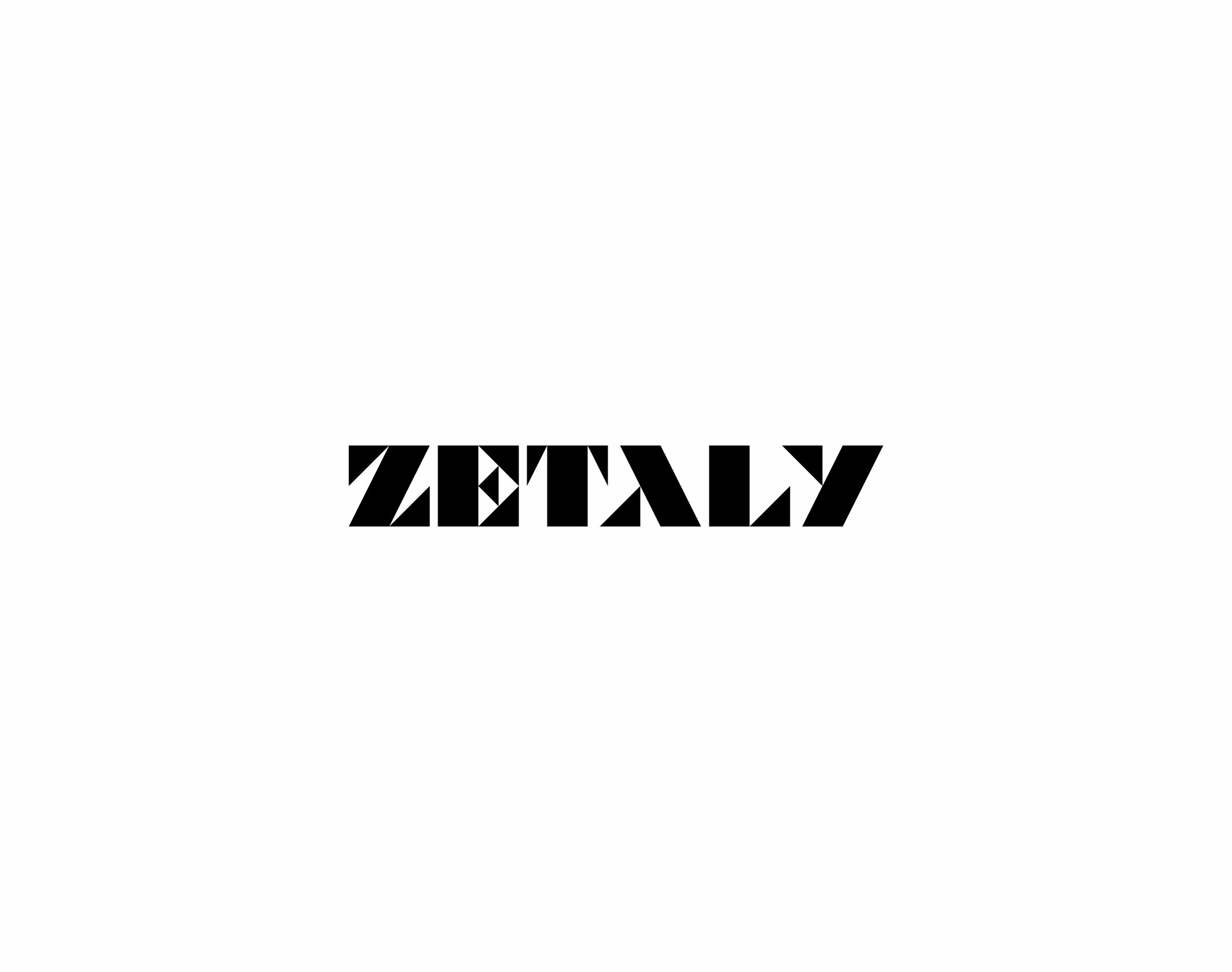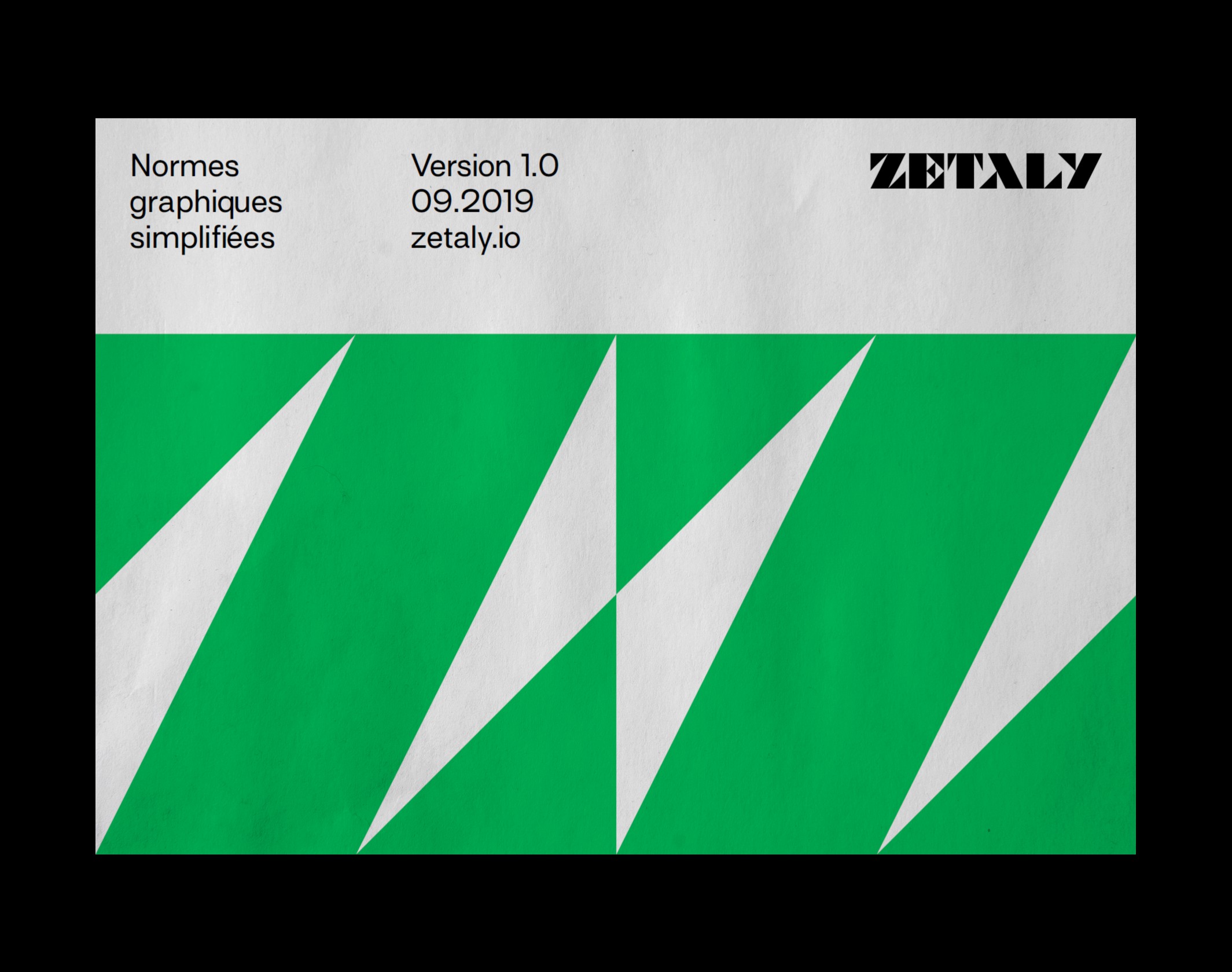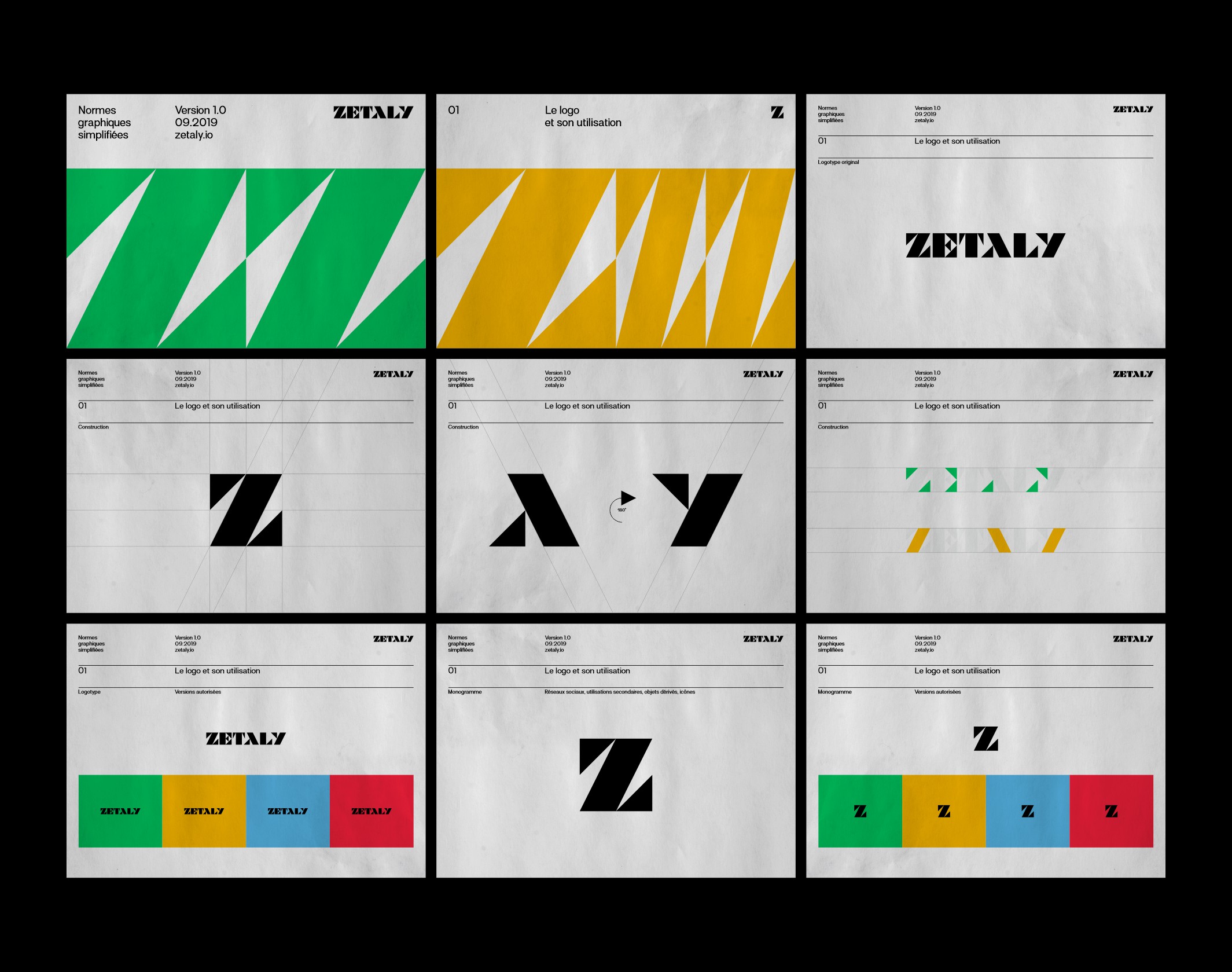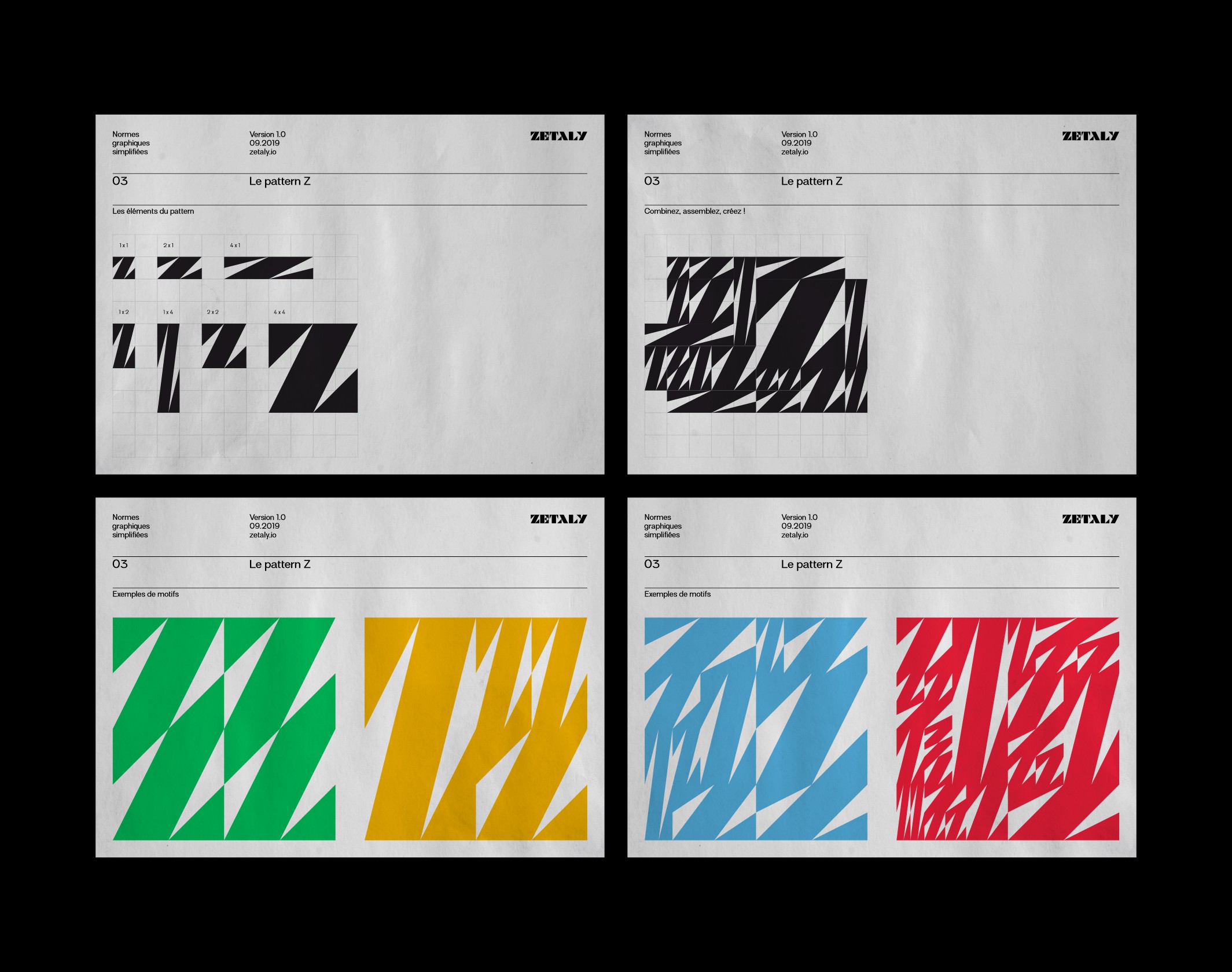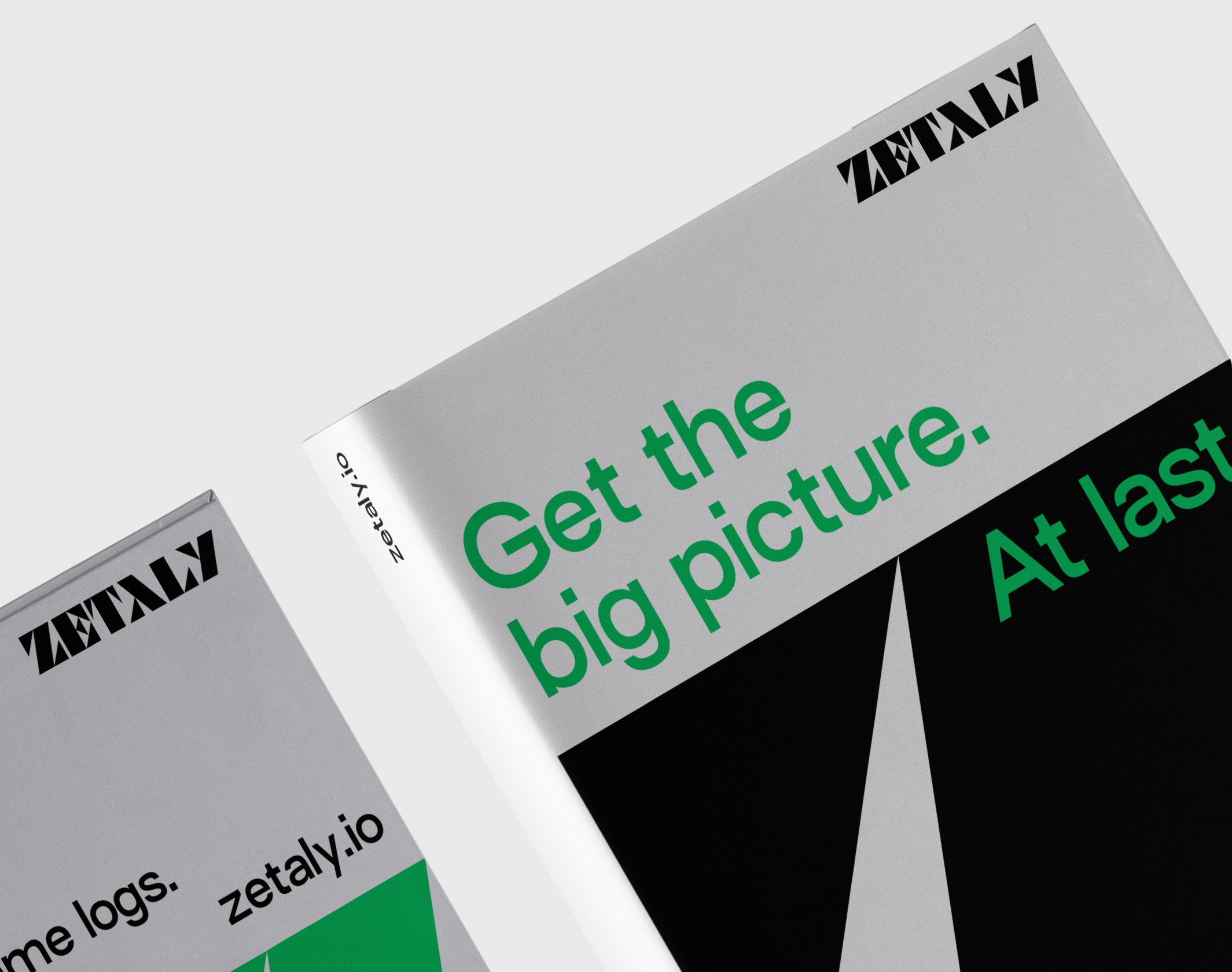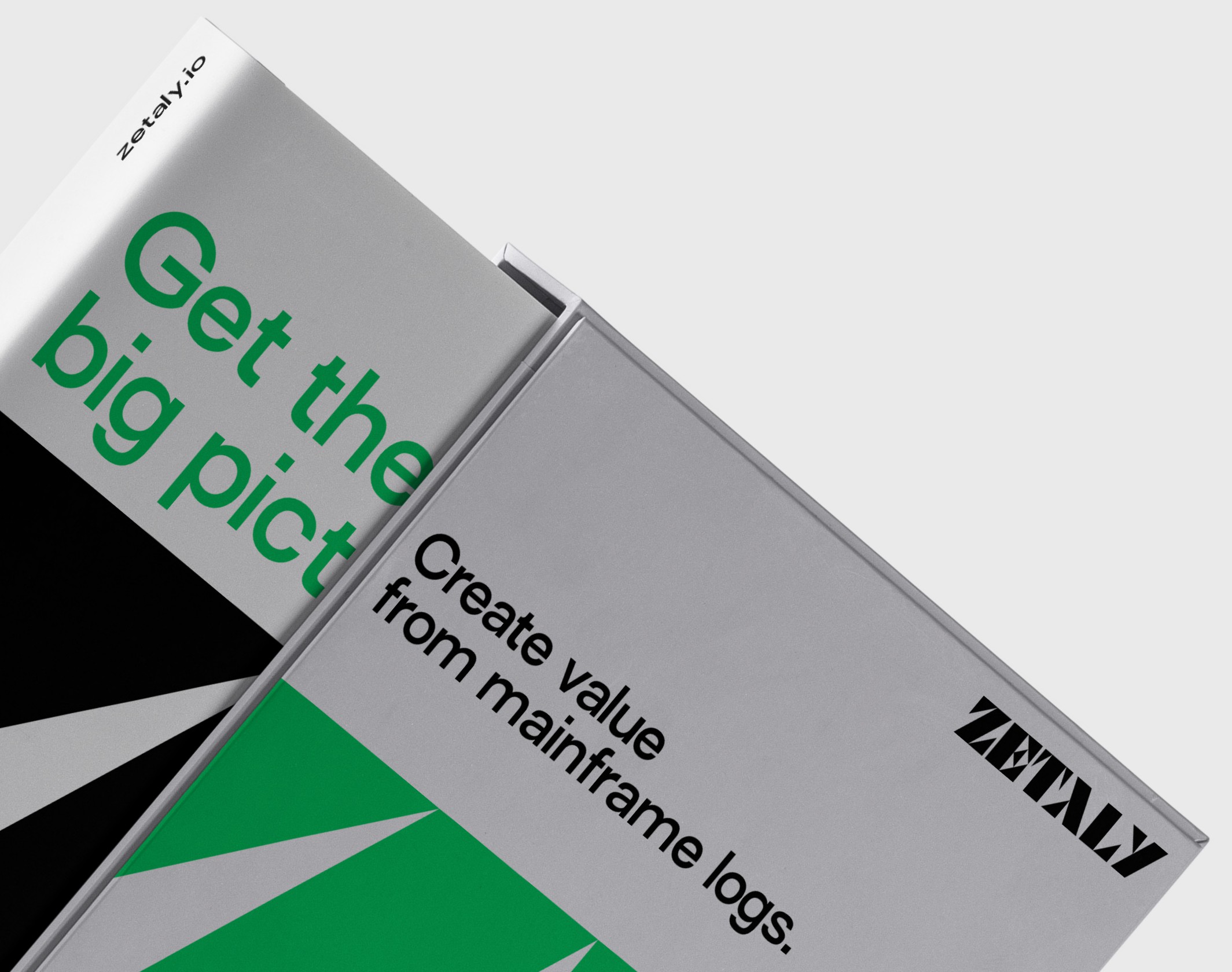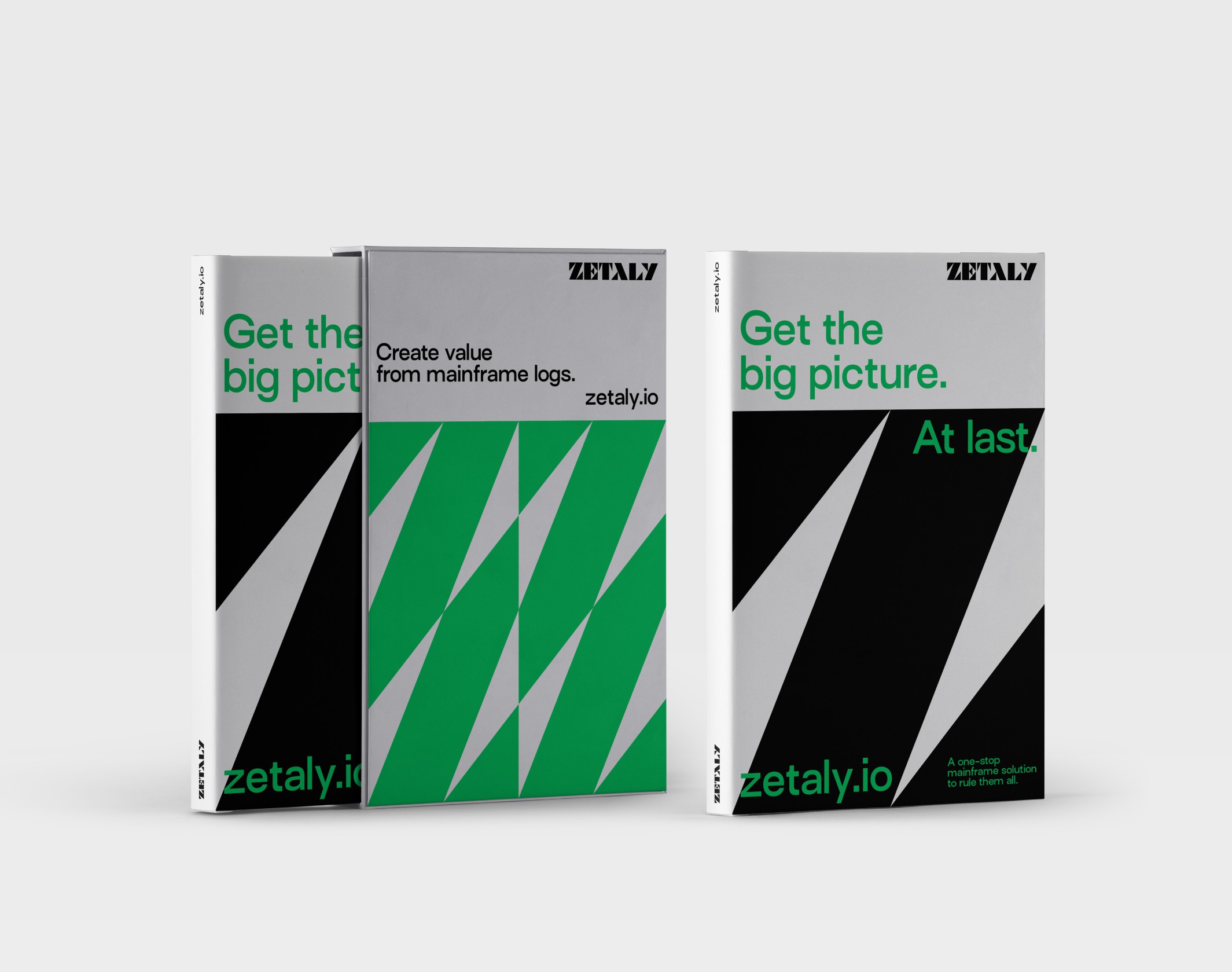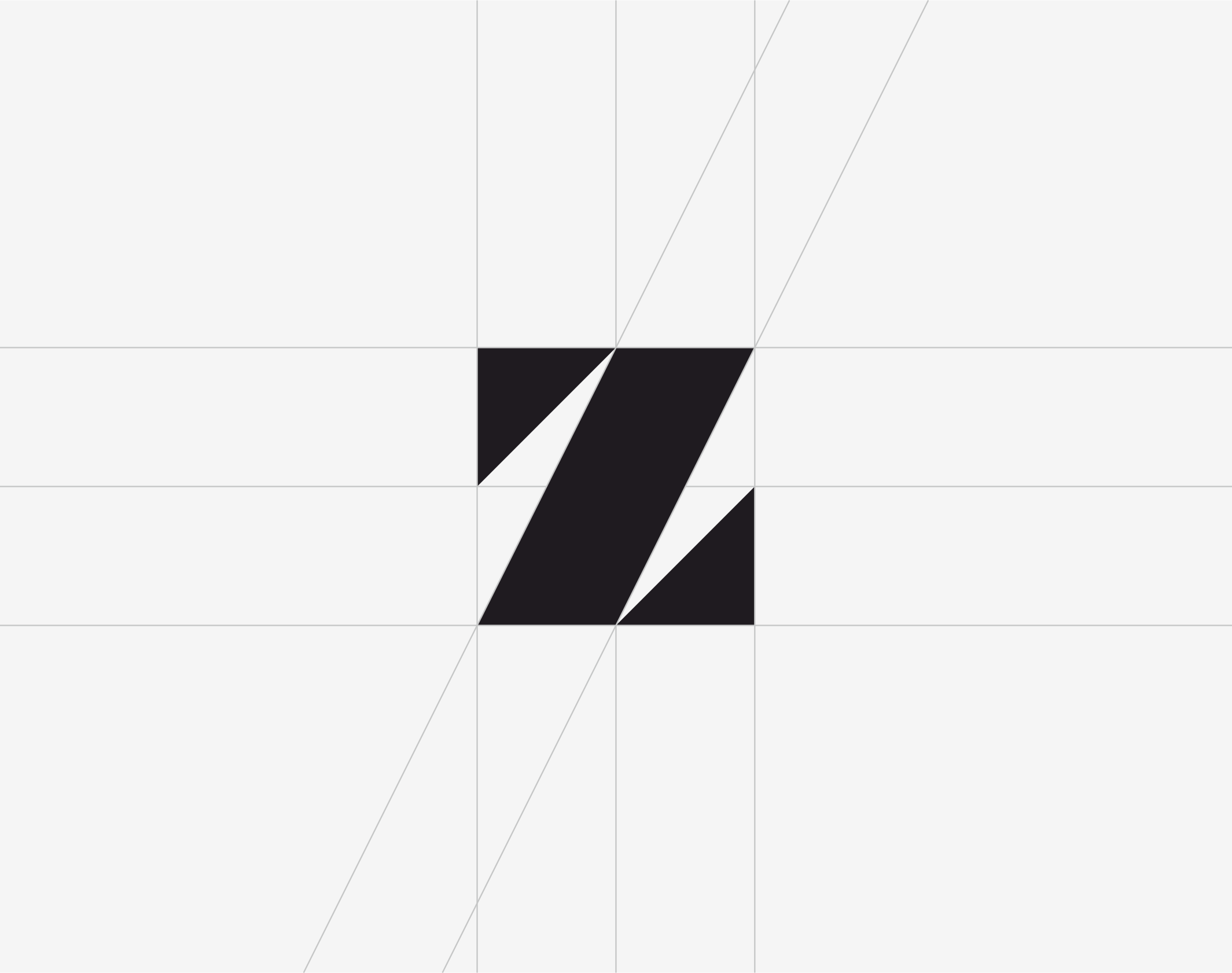
Zetaly
Zetaly, une solution unique pour valoriser les données z/OS, se dote d'une identité visuelle dynamique et autonome avec un logo typographique innovant
Zetaly est une émanation du groupe technologique Zcost, réputé pour ses solutions autour des systèmes z/OS (ordinateurs centraux à grande capacité de traitement, implantés notamment dans la bancassurance). Cette solution de dernière génération, unique au monde, permet d’exploiter de manière simple, claire et lisible toutes les données extraites de l’exploitation de ces systèmes complexes, et ainsi leur donner de la valeur à grande échelle. Nous avons été approchés pour donner à Zetaly une identité visuelle et ses fondamentaux graphiques.
Le logo typographique – conçu pour l’occasion – est basé sur des proportions géométriques permettant de créer un jeu infini de multiplications et d’additions de formes. Ainsi, nous avons livré un kit de monogrammes Z, permettant de créer sans limite des motifs graphiques, habillant les différents supports visuels de Zetaly, et ce de manière rapide et autonome. Le territoire graphique, tranché et électrique, est complété par le caractère AT Surt (Blaze Type), utilisé dans toutes ses graisses.